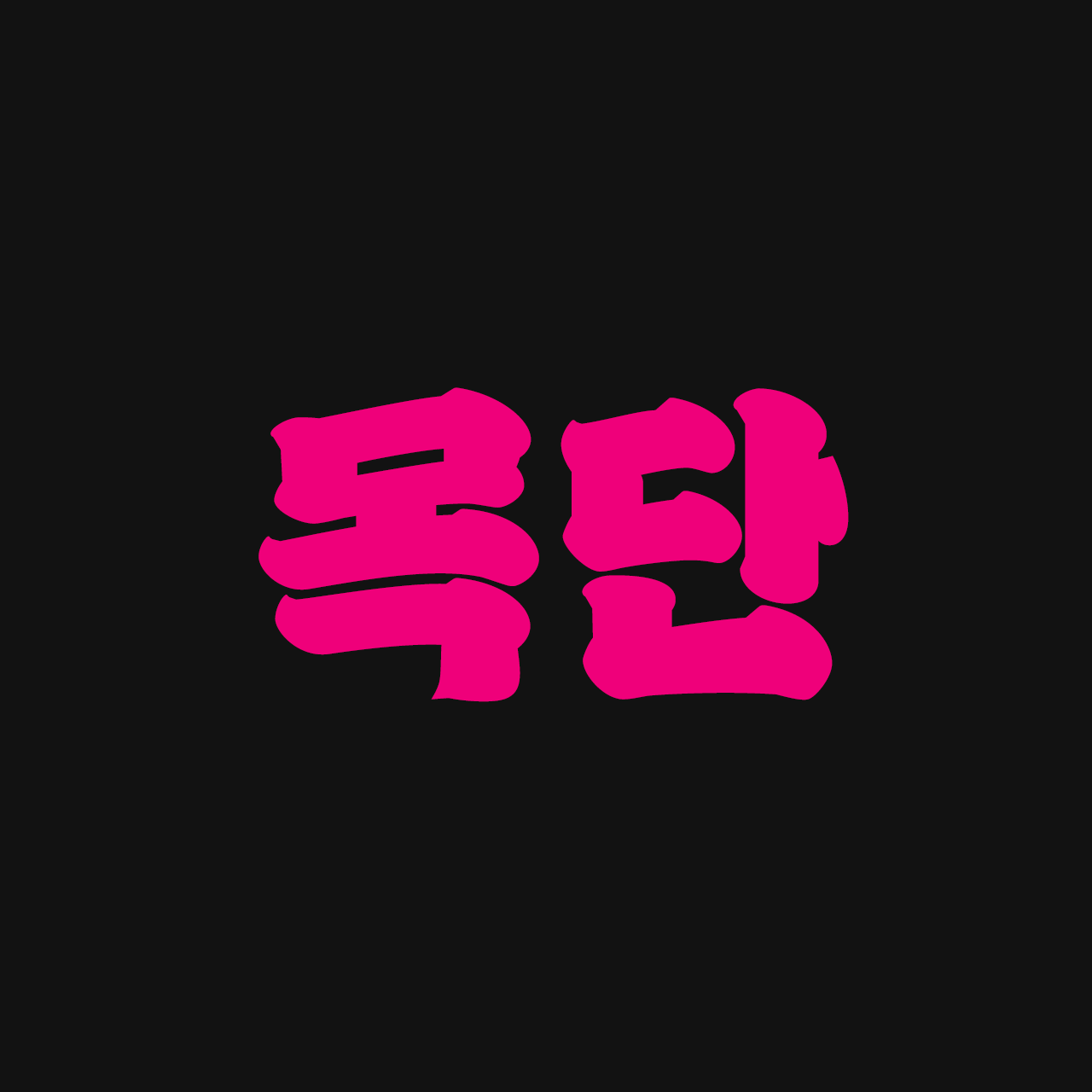
Sandoll 목단
목단은 '모란꽃'을 이르는 말입니다. 글자 내 풍부한 양감과 붓의 질감이 주는 화려함과 잘 어울리는 이름이지요.
산돌 목단의 컨셉은 굵은 붓으로 천천히 써 내려간 글씨입니다. 획이 매우 두껍다 보니 가독성보다는 글자가 유발하는 시각적 효과와 재미에 중점을 두고 제작하였습니다. 'ㅇ'의 상투와 'ㅅ'의 비침같이 힘차게 쓰여진 붓글씨의 흔적을 찾아보세요. 꽉 찬 인상, 그리고 손으로 쓴 글씨라는 맥락은 산돌 목단의 영문에서도 이어집니다. 영문 스크립트 폰트는 대부분 빠르고 경쾌하게 쓴 글씨이기 때문에, 느리게 쓴 목단의 글자와는 획의 속도감, 기울기 등에서 맞지 않는 부분이 많았습니다. 그래서 서양의 전통적인 손글씨 중 중세 블랙레터의 구조를 응용하여 대문자와 소문자 하단의 세리프에 대입하였습니다.
개성 강한 제목용 폰트 목단으로 강렬한 메시지를 전달해보세요.